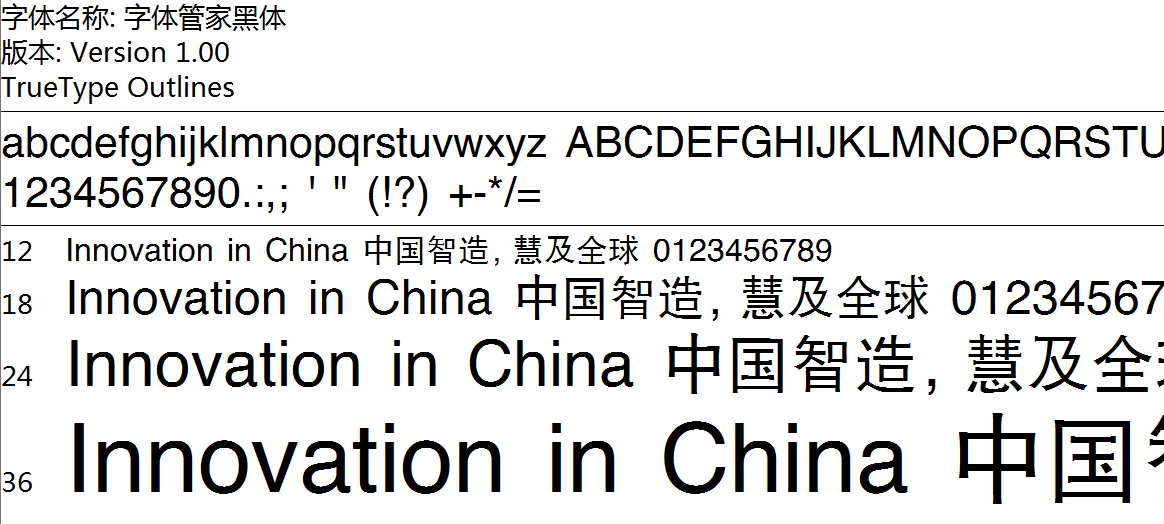
字體管家黑體.ttf 介紹
字體管家黑體.ttf是壹款非常漂亮的藝術字體,字體管家黑體.ttf廣泛用于各種書刊、畫冊的設計印刷中,字體管家黑體.ttf具有強烈的視覺沖擊力,字體管家黑體.ttf報紙和雜志和書籍中常用字體, 海報、個性促進品牌標志設計、字體設計、等環境,字體字體管家黑體.ttf的下載地點,字體管家黑體.ttf 從哪裏下載.字體管家黑體.ttf字體安裝。